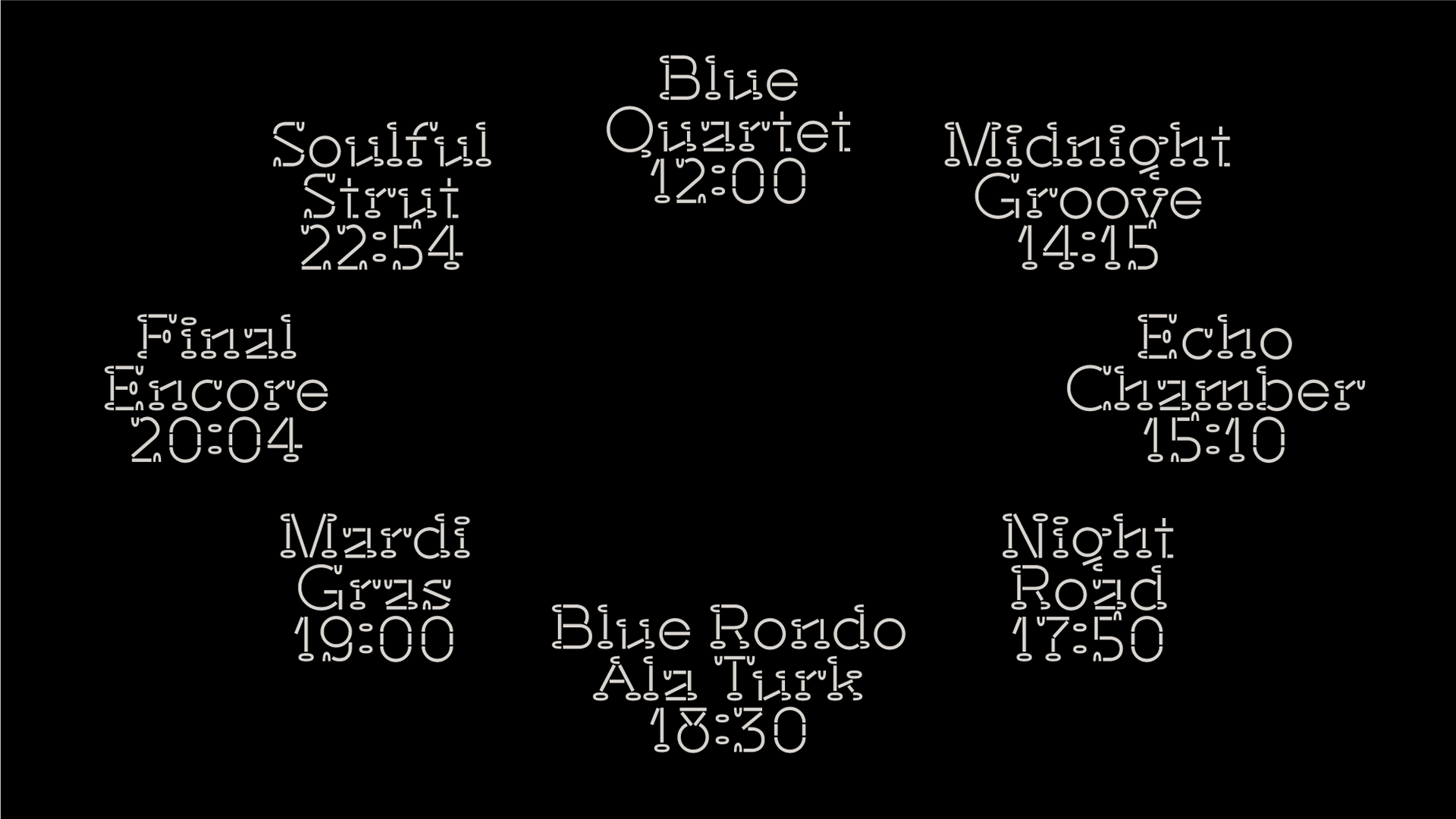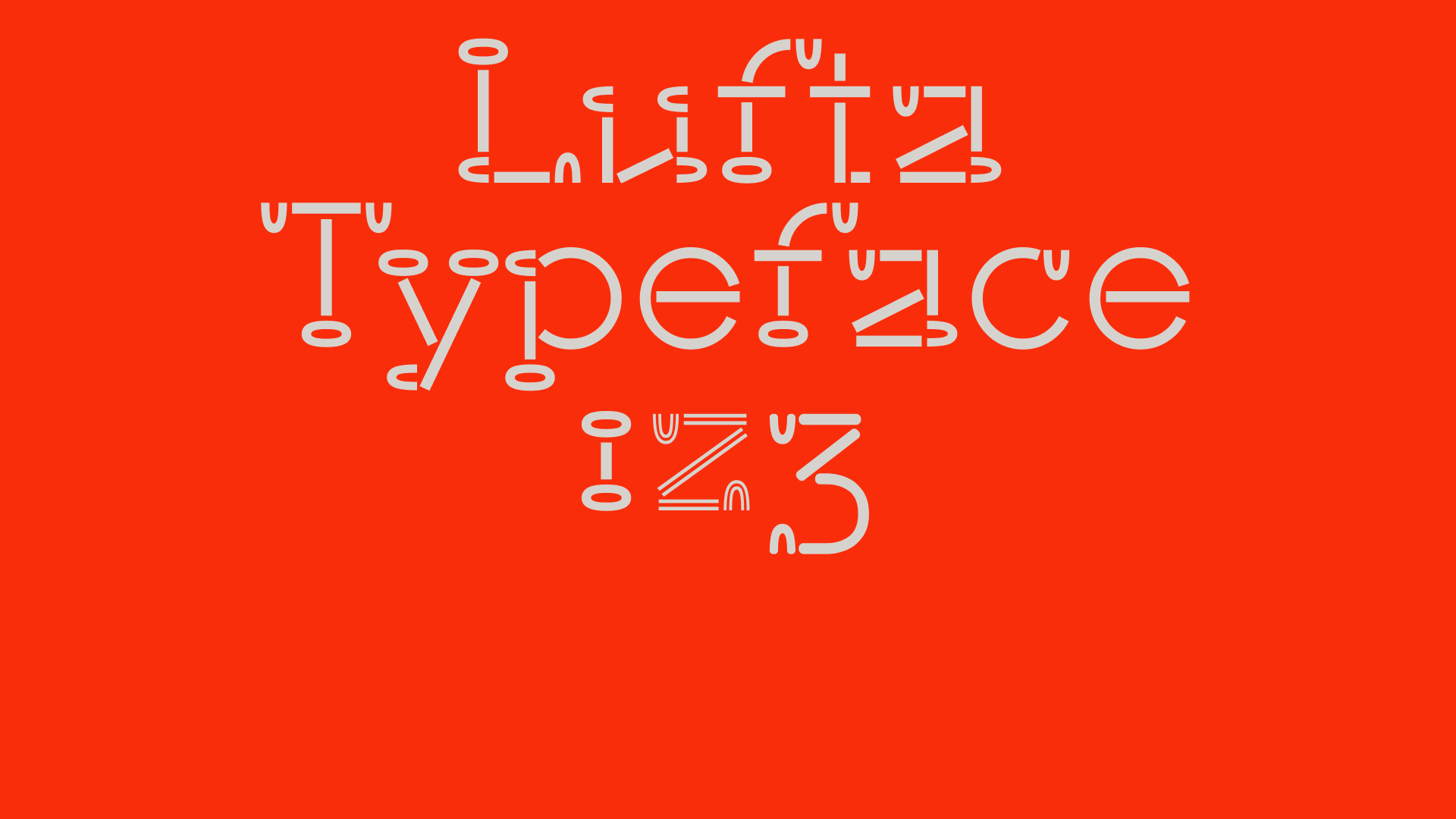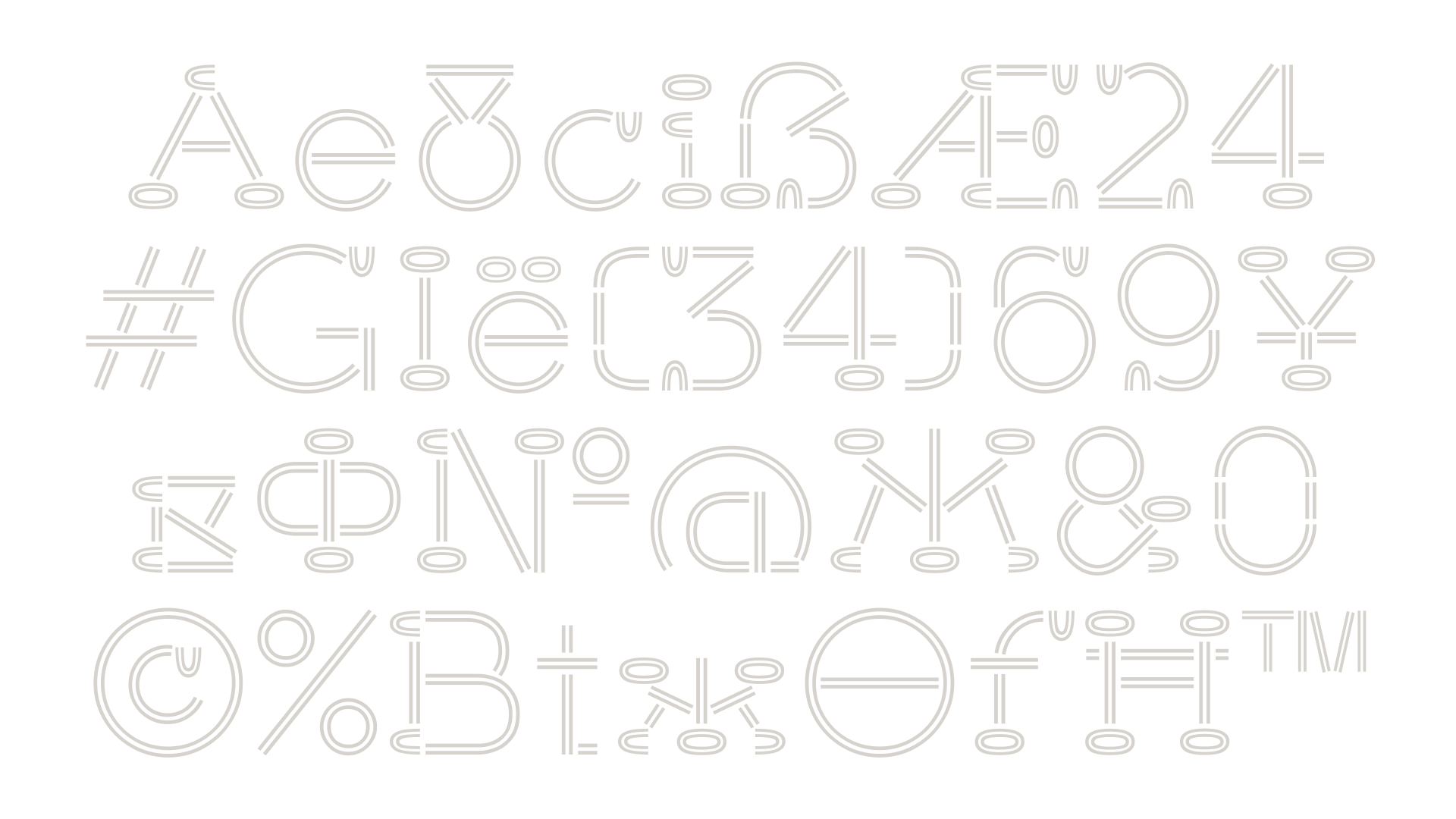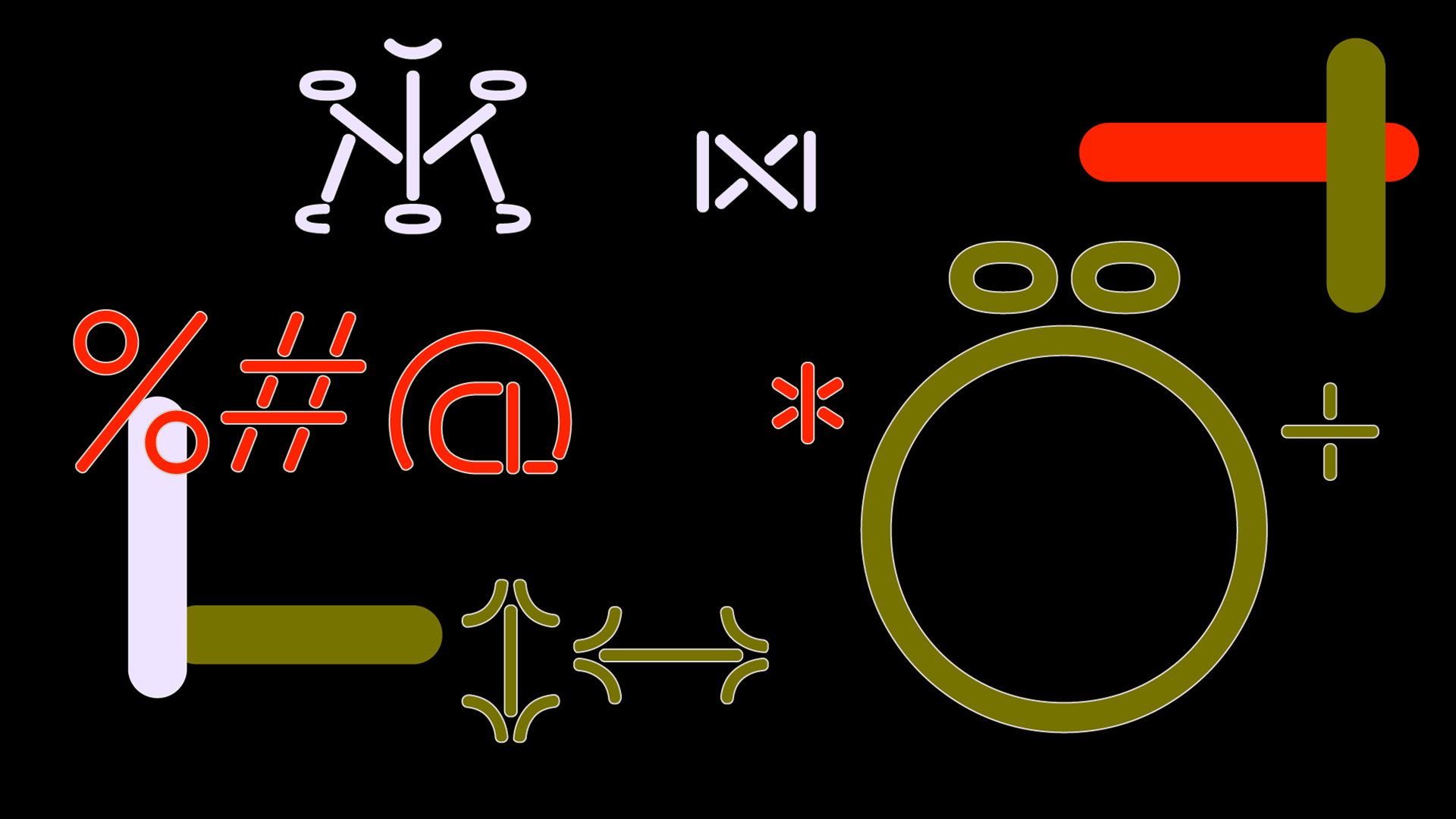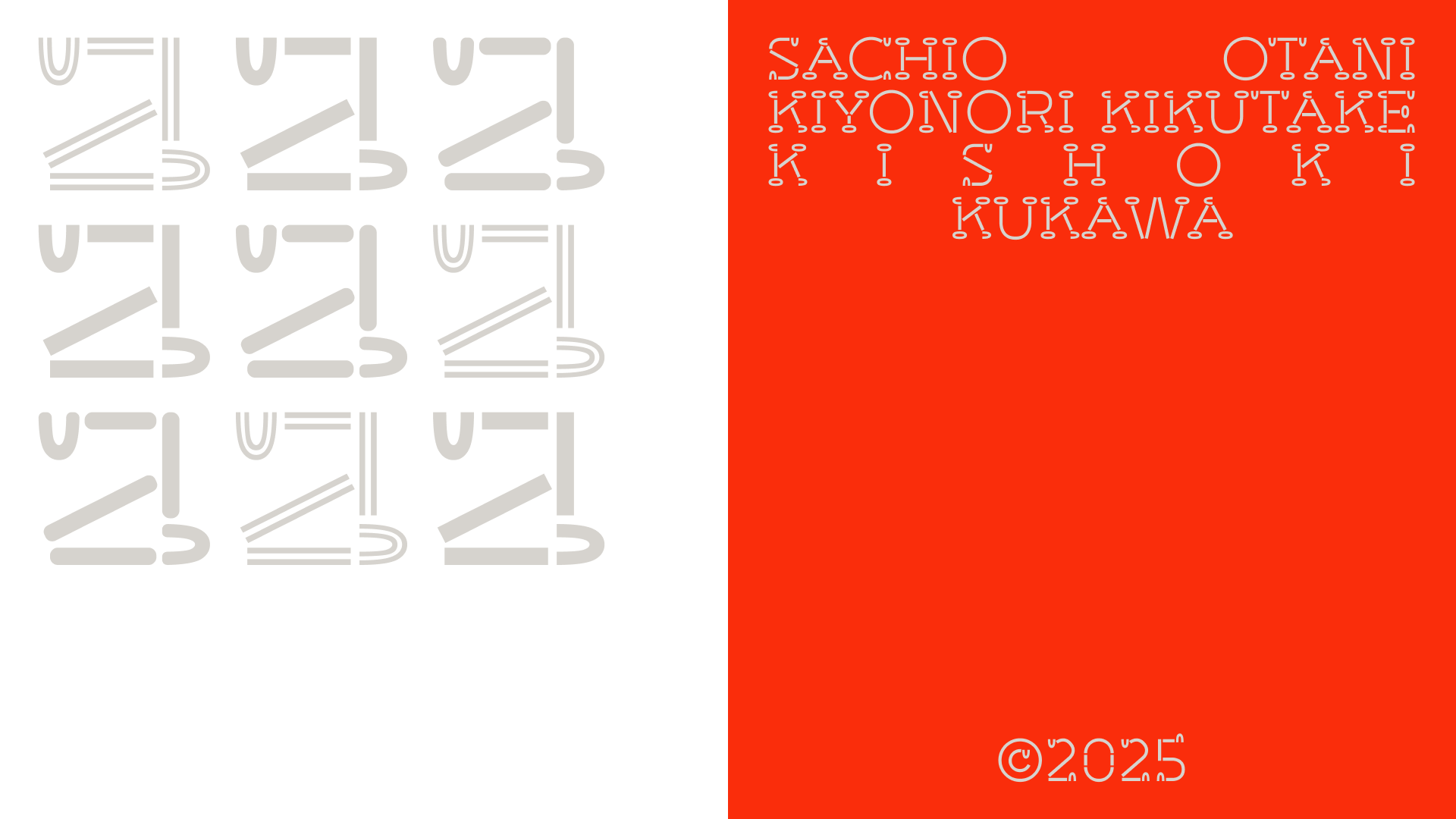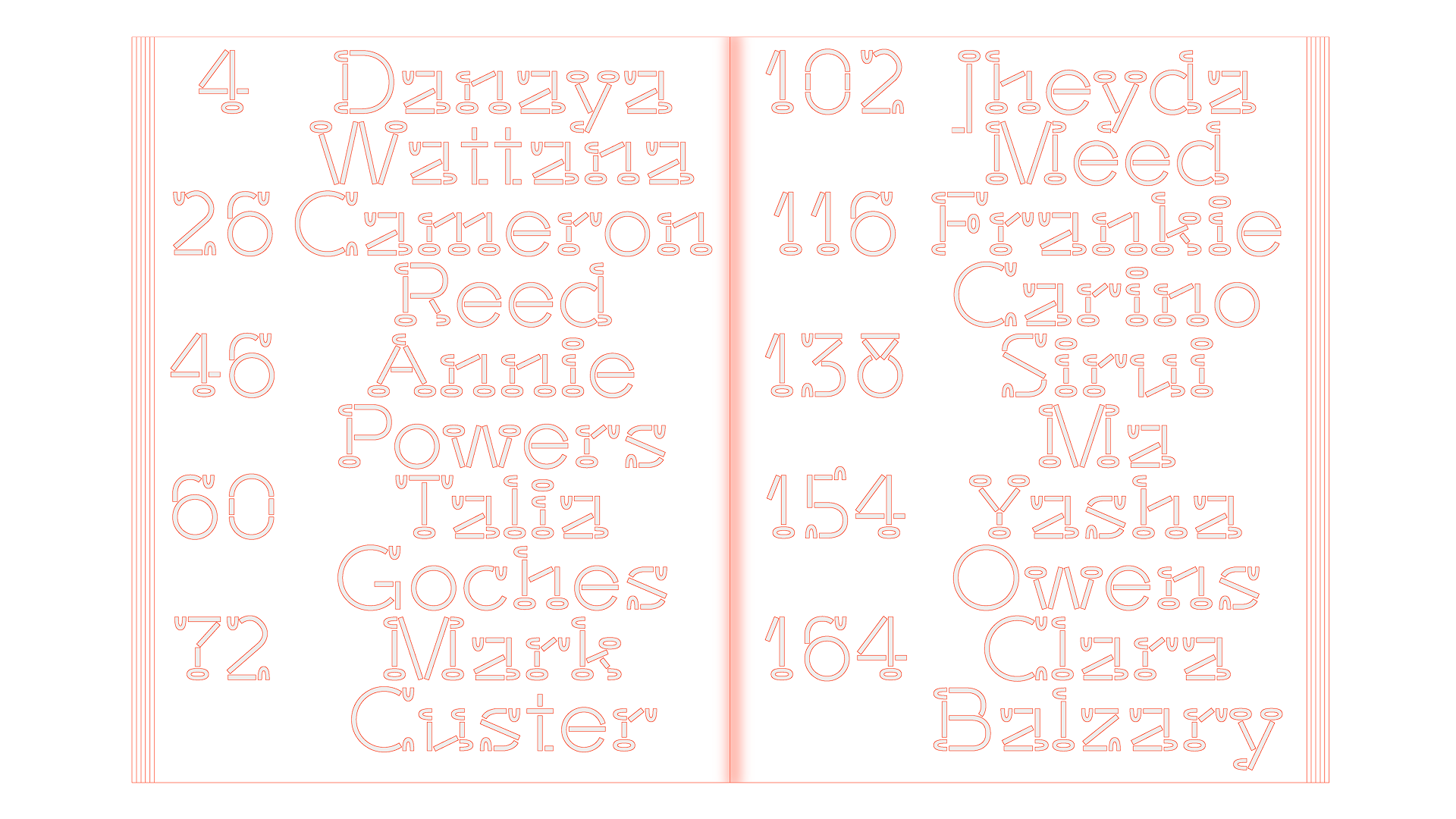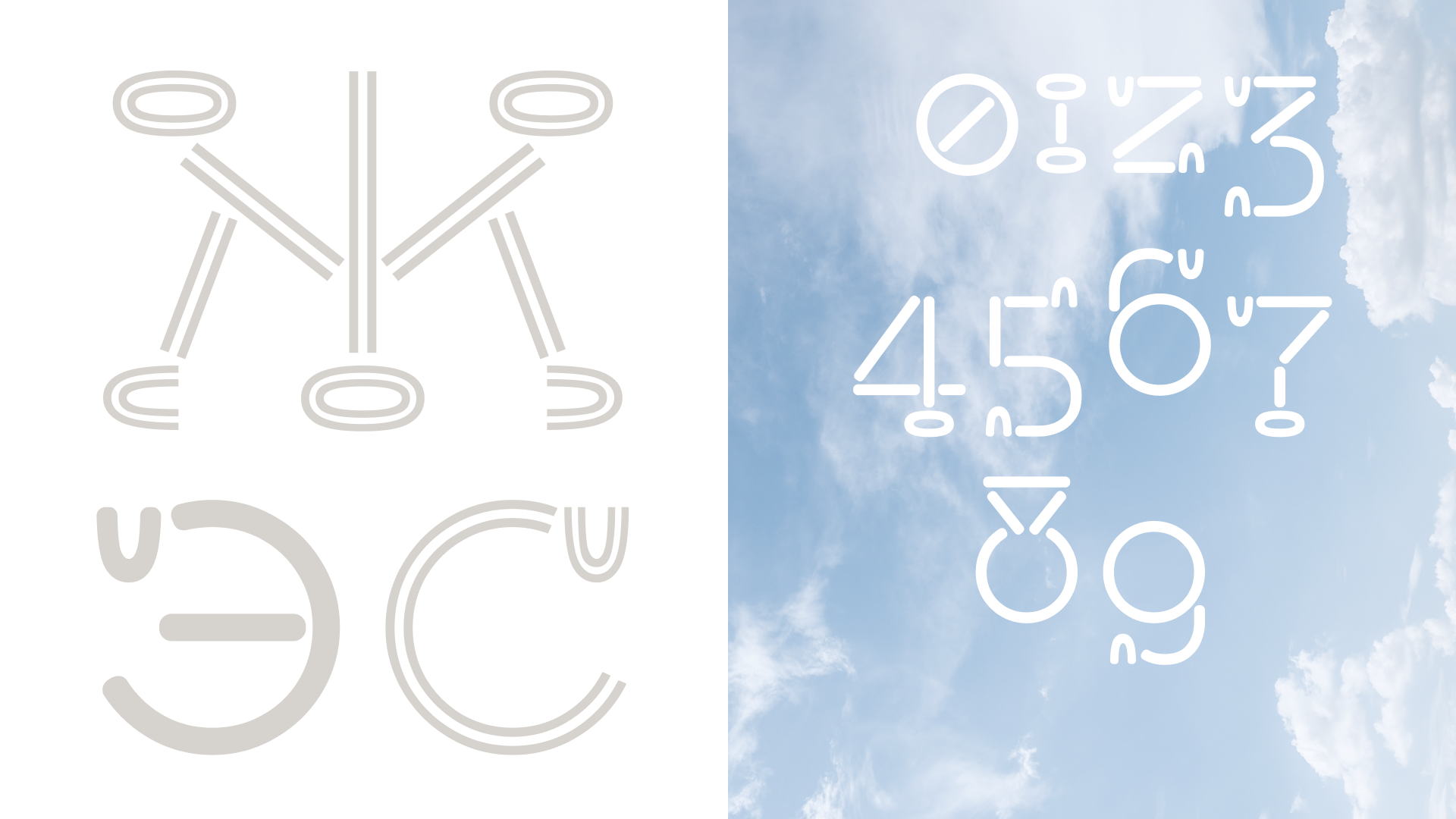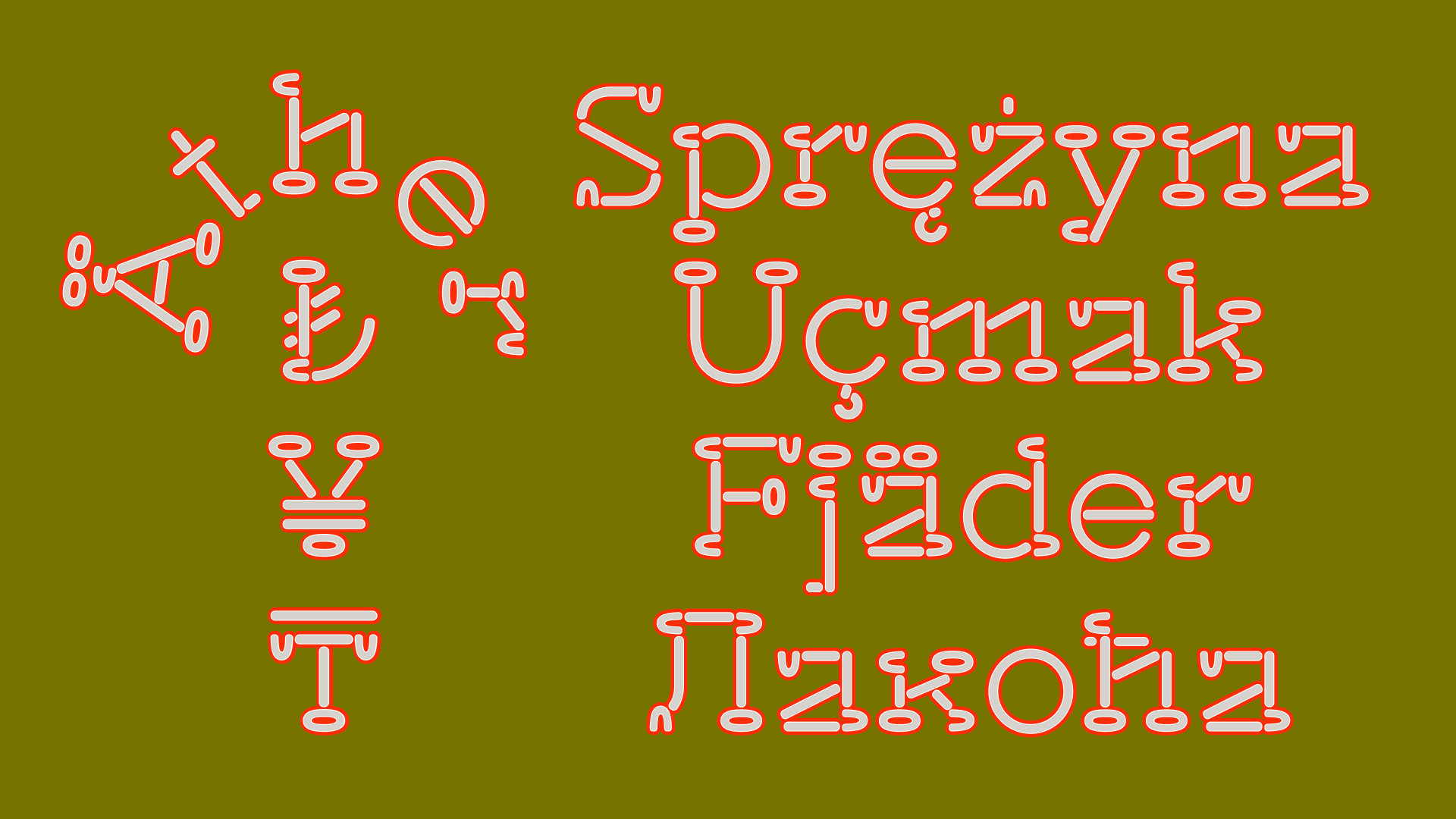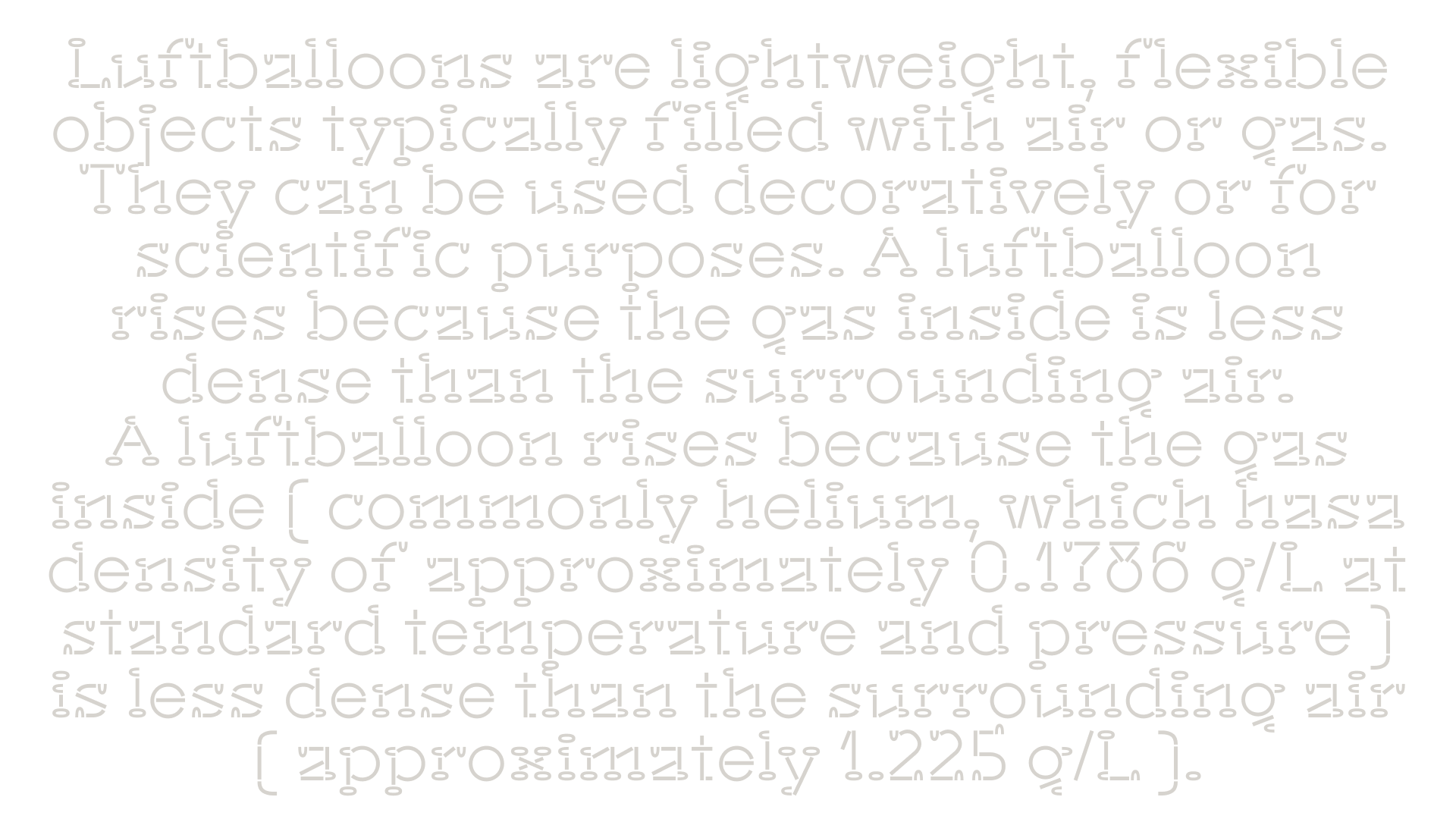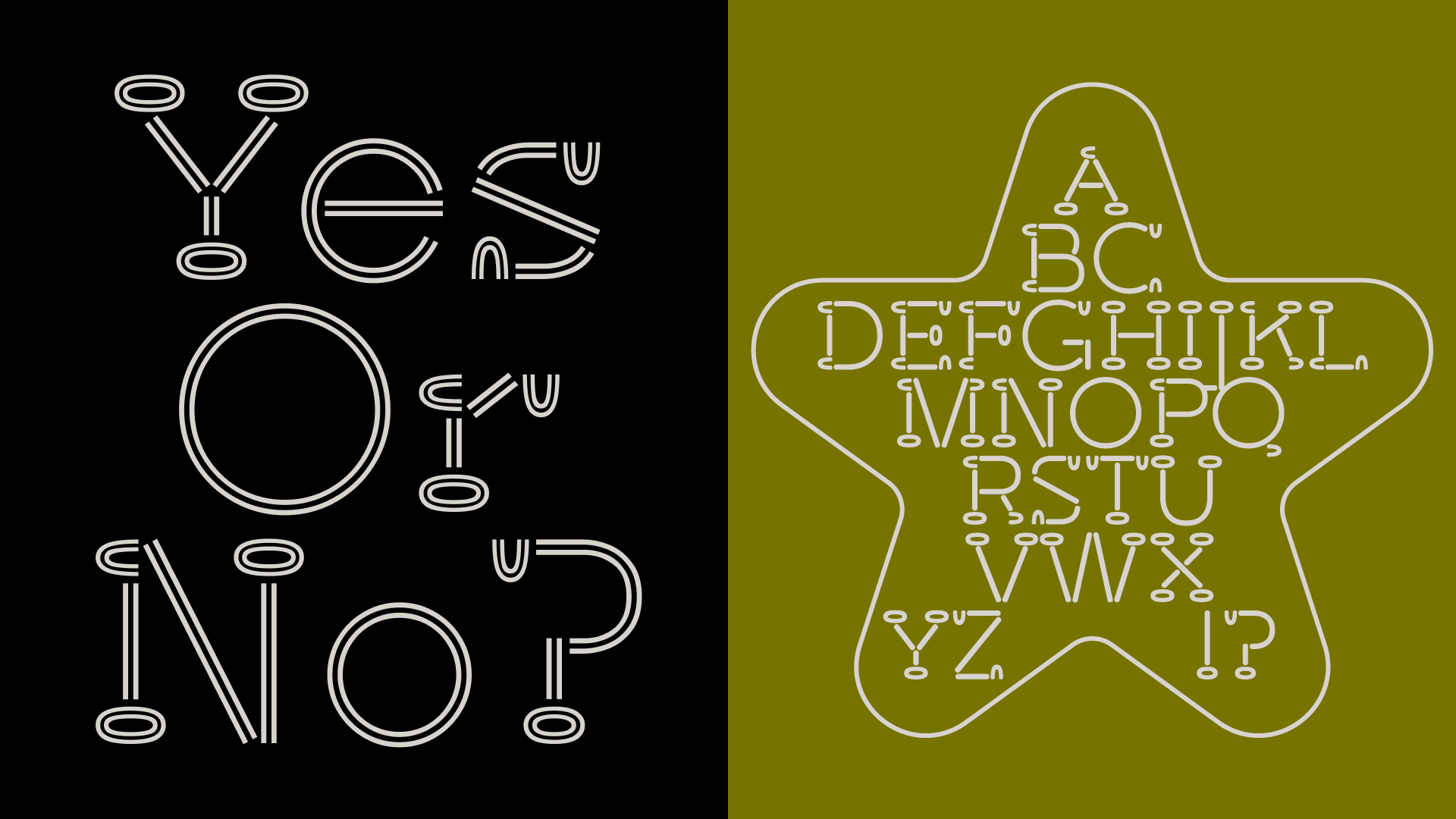
Lufta
Время от времени дизайнер Владимир Коломейцев присылает в телеграм-чат Playfaces надпись и предлагает участникам сделать леттеринг на её основе. С одной из таких надписей и начался шрифт Lufta. Унаследовав от прототипа только необычную форму засечек, он превратился в дружелюбную и почти трафаретную брусковую антикву, которая будет одинаково хорошо работать и на светоотражающих патчах для одежды, и в айдентике deep-tech стартапа, и в DIY-проектах (например, навигации по гаражной распродаже). В Lufta — три начертания: технологичное Normal, тёплое Rounded и напоминающее типографику музыкальных обложек 70-х — Doubled. Шрифт поддерживает расширенные латиницу и кириллицу (в том числе болгарскую), а ещё в нём два набора цифр.